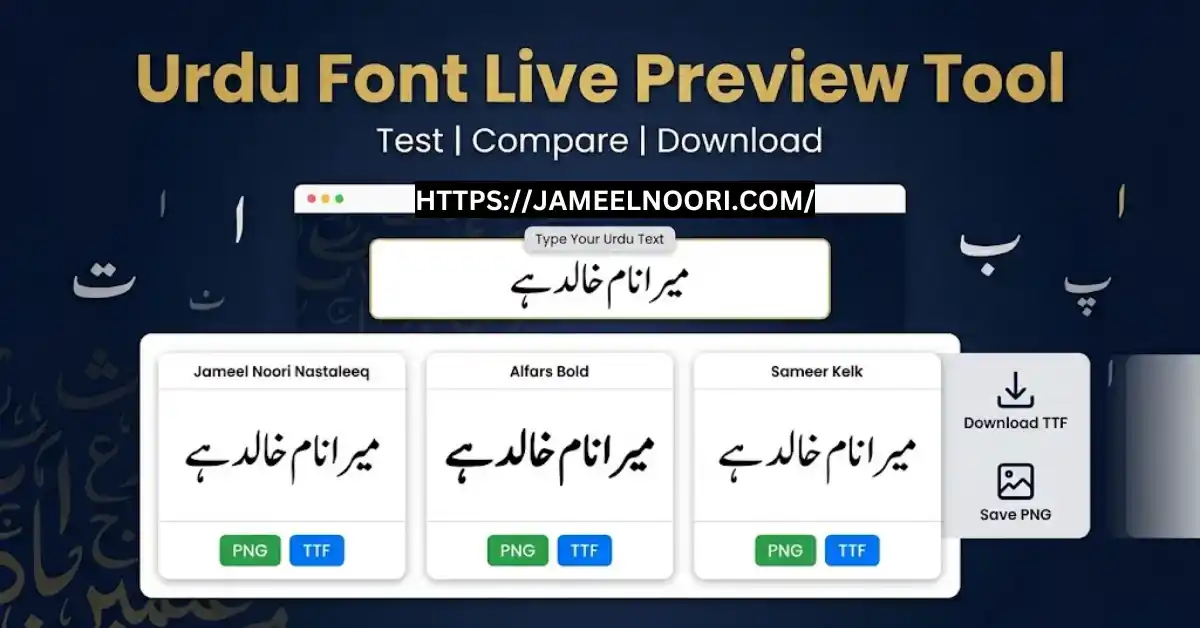
Urdu Font Live Preview Tool – Introduction
aap ne kabhi socha hai ke koi aisa tool ho jahan aap ek baar mein 200 se zyada Urdu fonts dekh sakte ho? jahan aap apna text likhein aur foran dekhein ke wo font mein kaisa lag raha hai? aisa tool ab available hai – Urdu Font Live Preview Tool.
yeh tool specially un designers, content creators, aur students ke liye banaya gaya hai jo free urdu fonts ke saath kaam karte hain. tool mein aap kuch seconds mein apna text test kar sakte hain aur dekh sakte hain ke kaunsa font aap ke project ke liye best hai.
main khud is tool ko use karta hun jab bhi naya project start karta hun. pehle mujhe fonts download karke install karne padte the, phir software mein test karne padte the. ab bas ek jagah par sab kuch dikh jata hai.
Tool Kaise Kaam Karta Hai? (Step by Step)
tool ka interface bohot simple hai. aap ko koi technical knowledge ki zaroorat nahi.
Step 1 – Text Likhein
sab se upar ek text box hai. wahan apna Urdu text likhein. aap example text bhi use kar sakte hain jaise “پاکستان زندہ باد” ya “میرا نام خالد ہے”. text change karte hi neeche sab fonts update ho jayenge.
Step 2 – Font Size Set Karein
slider hai jo 18px se lekar 72px tak size adjust karta hai. main text ke liye 32-40px acha rahta hai. headings ke liye 48-60px use kar sakte hain.
Step 3 – Colors Choose Karein
do color pickers hain. ek font color ke liye, ek background color ke liye. dark background par light text zyada readable hota hai. light background par dark text bhi acha lagta hai.
Step 4 – Style Apply Karein
bold, italic, aur underline buttons hain. aap chahe to text bold kar sakte hain, ya italic, ya dono. underline mostly headings ke liye use hota hai.
Step 5 – Compare Fonts
neeche scroll karte hi aap ko sab fonts dikhne lagenge. har font ka apna card hai. aap dekh sakte hain ke aap ka text us font mein kaisa lag raha hai.
Tool Mein Kaun Kaun Se Fonts Hain?
tool mein 200+ popular Urdu fonts hain. kuch important fonts ka overview:
Jameel Noori Nastaleeq – yeh font traditional calligraphy style mein hai. agar aap poetry, Islamic content, ya formal documents bana rahe hain to yeh best option hai. is font ki history 1981 se start hoti hai jab Ahmad Mirza Jamil ne Noori Nastaleeq design kiya tha.
Alfars Bold – yeh bold aur impactful font hai. headlines, posters, aur branding ke liye perfect hai. door se bhi clear dikhta hai.
Sameer Kelk Regular – clean aur readable font hai. articles, blogs, aur body text ke liye best hai. zyada der padhne se aankhon par pressure nahi padta.
Alqalam Ferdaos – stylish calligraphy font hai. wedding cards, event posters, aur creative designs ke liye use hota hai.
Zafar Urdu Font – elegant design hai. formal documents aur certificates ke liye acha hai.
Ahmed Urdu Font – simple aur clear font hai. educational material aur children books ke liye suitable hai.
Kurdish Unicode – multi-language support hai. regional content ke liye use kar sakte hain.
Al-Majeed Quranic Regular – Quranic style font hai. Islamic publications ke liye best hai.
Shamsheer Unicode – bold aur modern font hai. digital LED boards aur social media posts ke liye acha hai.
Urdu Naskh Unicode – clean aur professional font hai. news websites aur magazines mein use hota hai.
SF Koonj Regular – stylish aur unique font hai. creative designs ke liye best.
Yeh Tool Kis Liye Use Karein?
Time Bachane Ke Liye
pehle aap ko font download karna padta tha, install karna padta tha, phir software mein ja kar test karna padta tha. agar font pasand nahi aata to dobara. is tool mein ek hi jagah par sab kuch test ho jata hai.
Comparison Ke Liye
jab aap ek saath multiple fonts dekhte hain to comparison bohot asaan ho jata hai. aap dekh sakte hain ke kaunsa font zyada readable hai, kaunsa zyada stylish hai, kaunsa aap ke brand ke liye suitable hai.
Client Approval Ke Liye
agar aap kisi client ke liye kaam kar rahe hain to aap unhe tool ka link bhej sakte hain. wo khud dekh sakte hain ke different fonts mein design kaisa lag raha hai. is se approval process fast ho jata hai.
Font Download Karne Se Pehle Test Ke Liye
font download karne se pehle preview dekh lena acha hai. kabhi kabhi font online acha lagta hai lekin actual mein utna acha nahi hota. tool mein pehle test kar sakte hain.